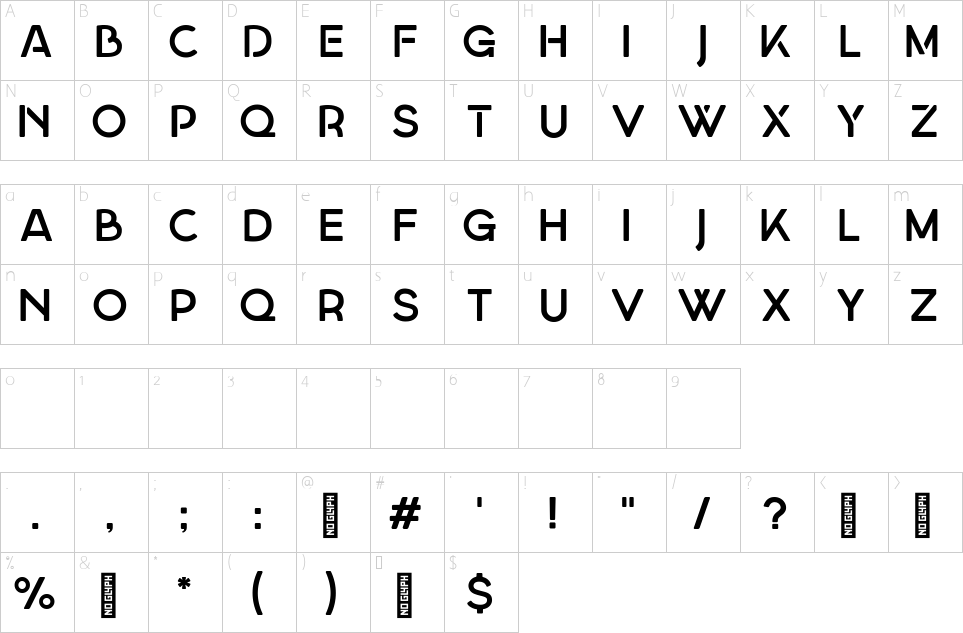
Georgina Font – Fonte Grátis
Georgina Font
A Georgina é uma fonte moderna e elegante que se destaca na categoria das fontes gratuitas. Desenvolvida pelo designer Phitradesign, essa tipografia já foi baixada 8.845 vezes. Com linhas arredondadas e um estilo clean, a Georgina oferece beleza clara que combina perfeitamente com diversos estilos de design gráfico. Seja para trabalhos visuais de escritório ou criações digitais, essa fonte garante uma aparência sólida e profissional sem comprometer o conforto do olhar. Não perca tempo: descubra por si mesmo a diferença que a Georgina pode fazer em seus projetos design.